Baklan Font — promo
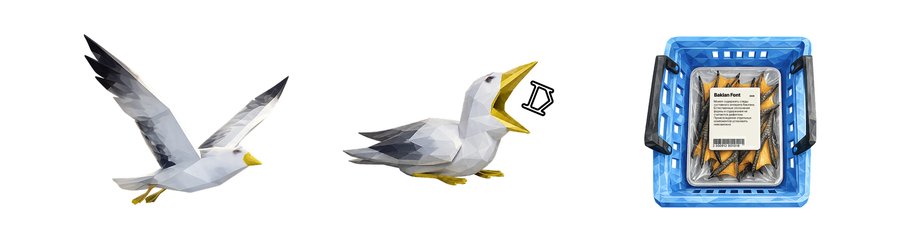
Три стадии существования баклана: полёт, поглощение, упаковка. символизирующие жизненный цикл шрифта: вдохновение, потребление, монетизация.
Концепция
Ролик использует язык видеоигр как метафору коллекционирования. Буквы превращаются в игровые артефакты, которые баклан собирает без какой-либо цели, кроме самого процесса накопления.
Неспособность остановиться приводит к разрушению персонажа. Финальная сцена раскрывает шутку: шрифт основан на форме лап баклана, вся история — буквальный случай каннибализма внутри типографической системы.